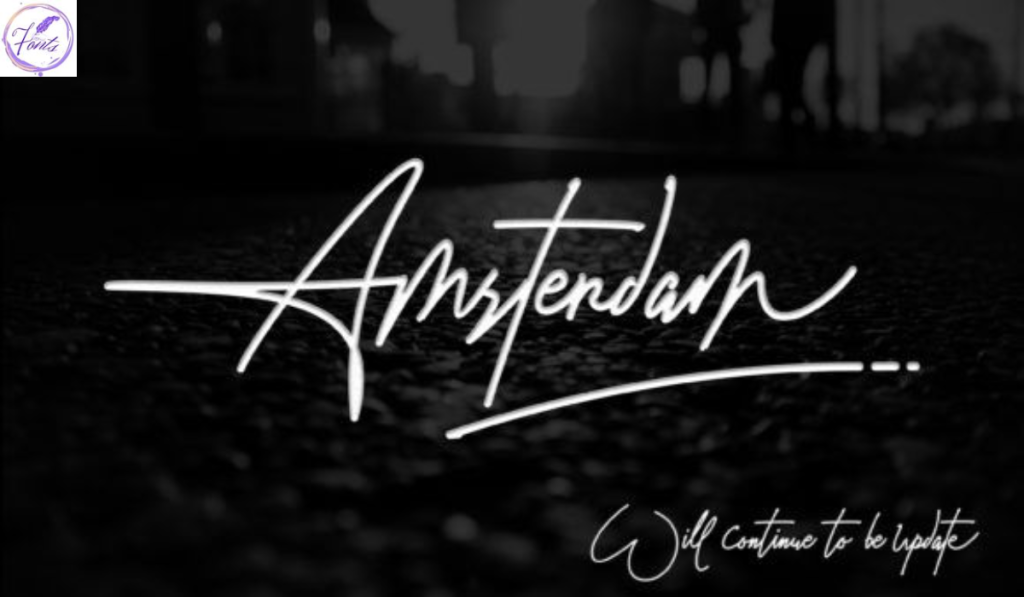
Amsterdam font việt hóa
Tác giả: Billy Argel
Ngày phát hành: 2004
Ngôn ngữ: Tiếng Việt, Tiếng Anh, và nhiều ngôn ngữ khác
Bộ Font: Amsterdam
Phân loại: cá tính, độc đáo, hiện đại, thanh lịch
Kiểu chữ: script
Amsterdam font là một font chữ nổi bật với phong cách cổ điển nhưng vẫn hiện đại, tạo nên sự hài hòa và tinh tế cho các thiết kế của bạn. Được ra mắt vào năm 2004, font này được thiết kế bởi Billy Argel, nhằm mang lại trải nghiệm mới mẻ cho người dùng. Với các đường nét thanh mảnh và uyển chuyển, amsterdam font phù hợp với nhiều loại dự án từ thiết kế web, quảng cáo, đến in ấn. Đặc biệt, font này đã được Việt hóa đầy đủ, giúp bạn dễ dàng sử dụng trong các dự án tiếng Việt mà không gặp vấn đề về hiển thị ký tự.
Đánh giá amsterdam font
Amsterdam font được đánh giá cao bởi các chuyên gia trong ngành thiết kế nhờ vào tính ứng dụng và thẩm mỹ của nó. Font này không chỉ dễ đọc mà còn mang lại cảm giác trang nhã và chuyên nghiệp. Một số tạp chí thiết kế nổi tiếng đã bình chọn amsterdam font là một trong những font chữ đẹp nhất cho các dự án sáng tạo. Với khả năng hiển thị tốt trên cả các thiết bị kỹ thuật số và bản in, font này giúp bạn truyền tải thông điệp một cách hiệu quả. Nếu bạn đang tìm kiếm một font chữ đa năng và tinh tế, amsterdam font chắc chắn là sự lựa chọn hoàn hảo.